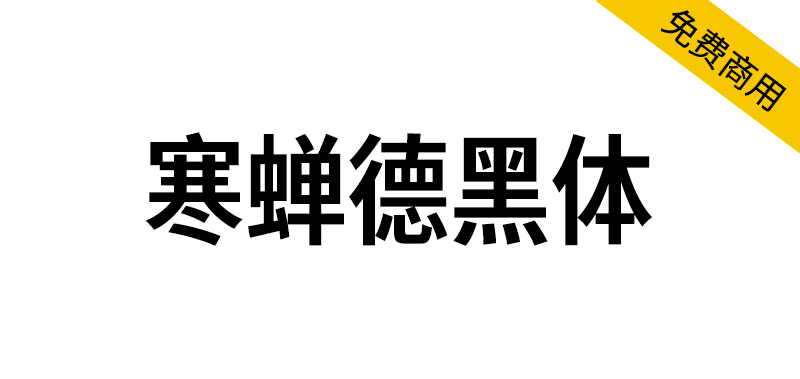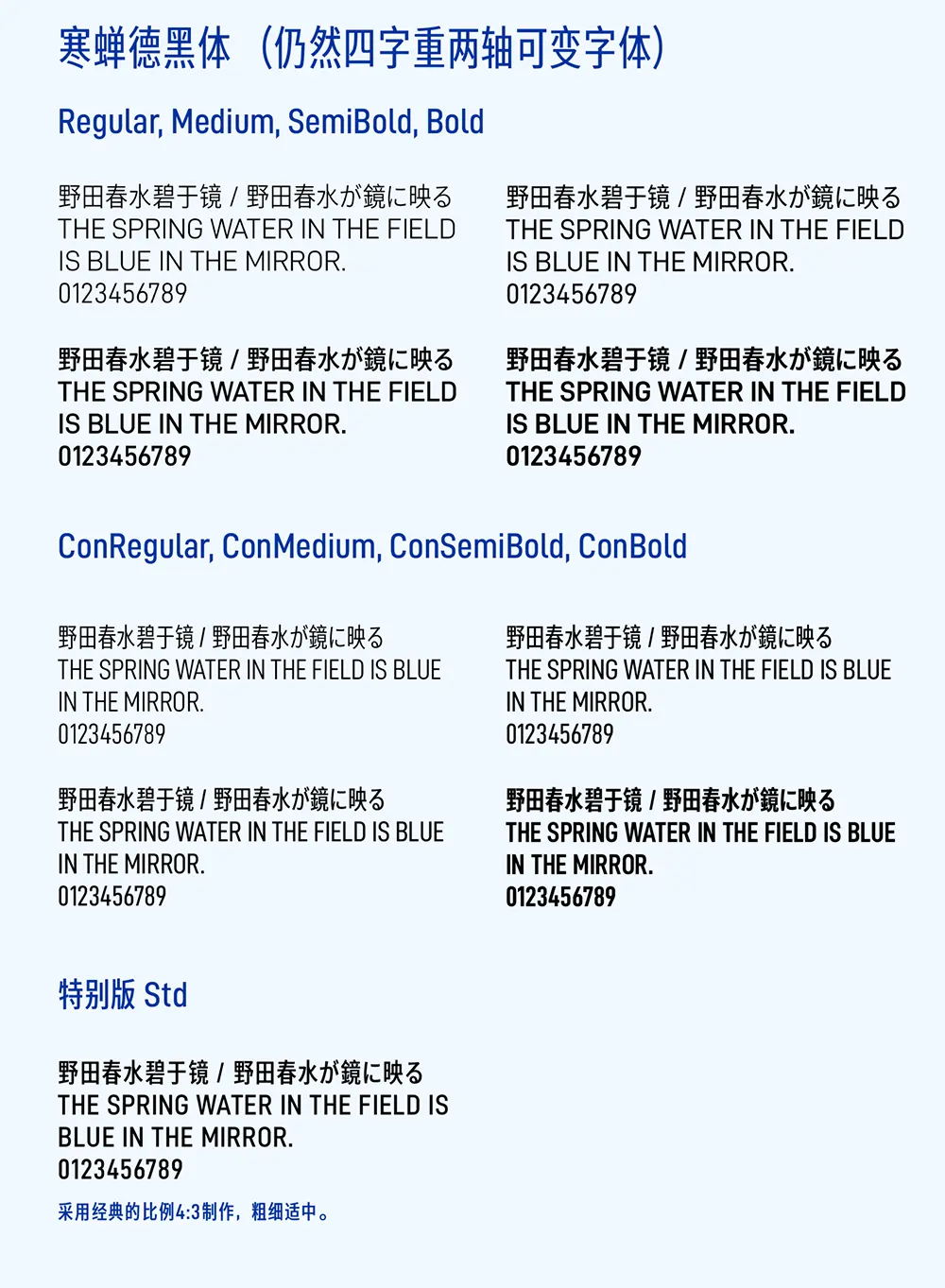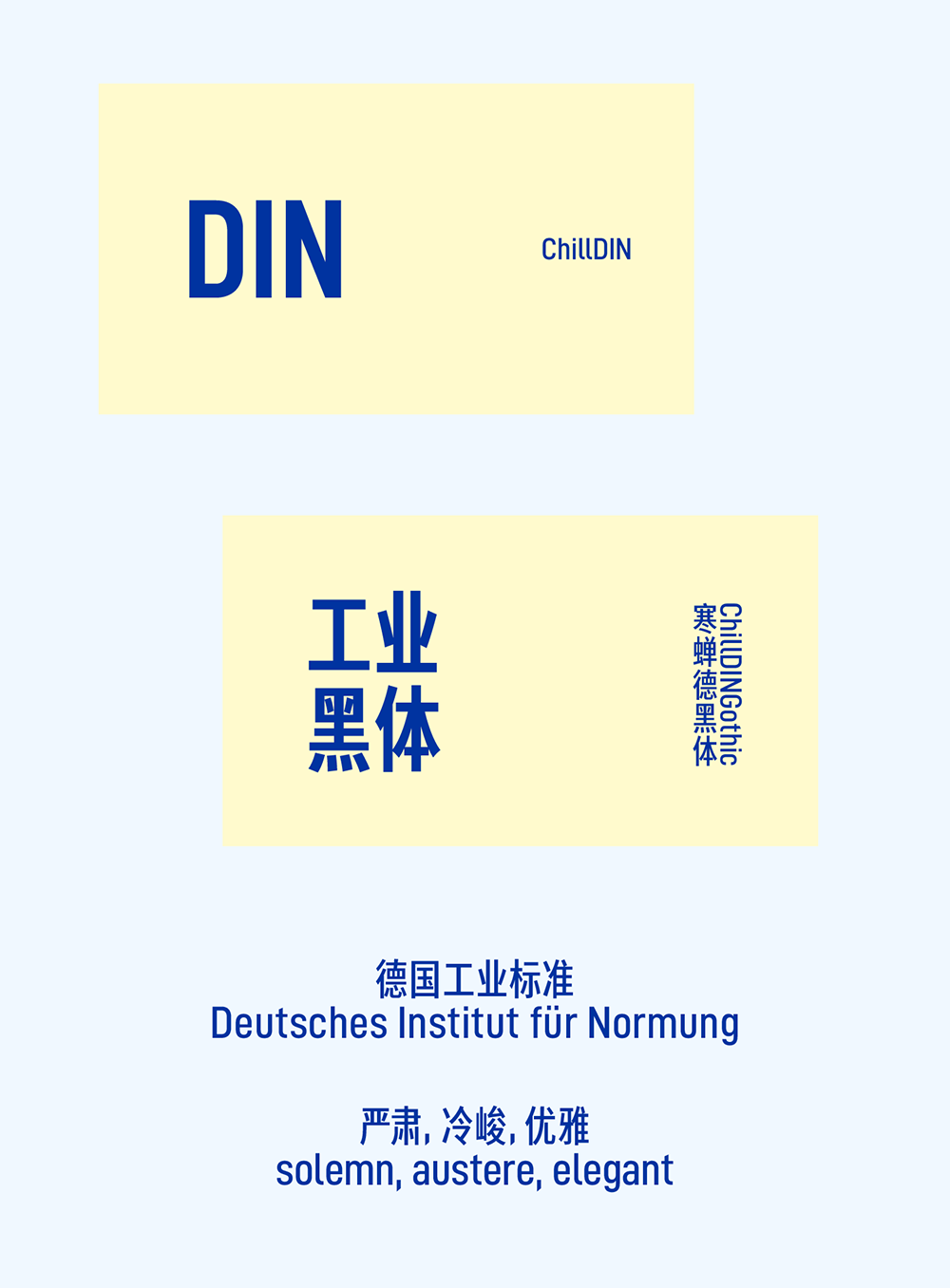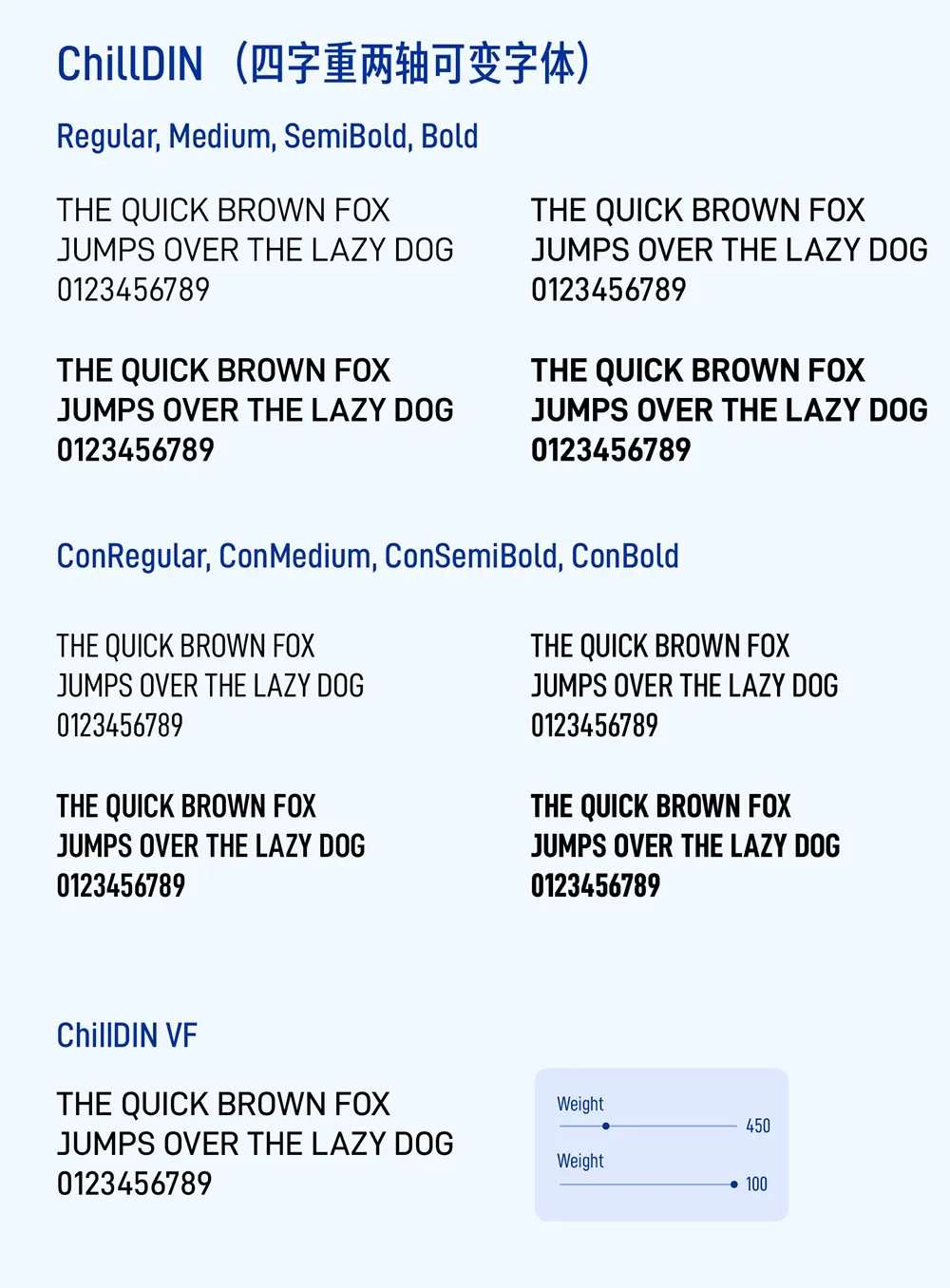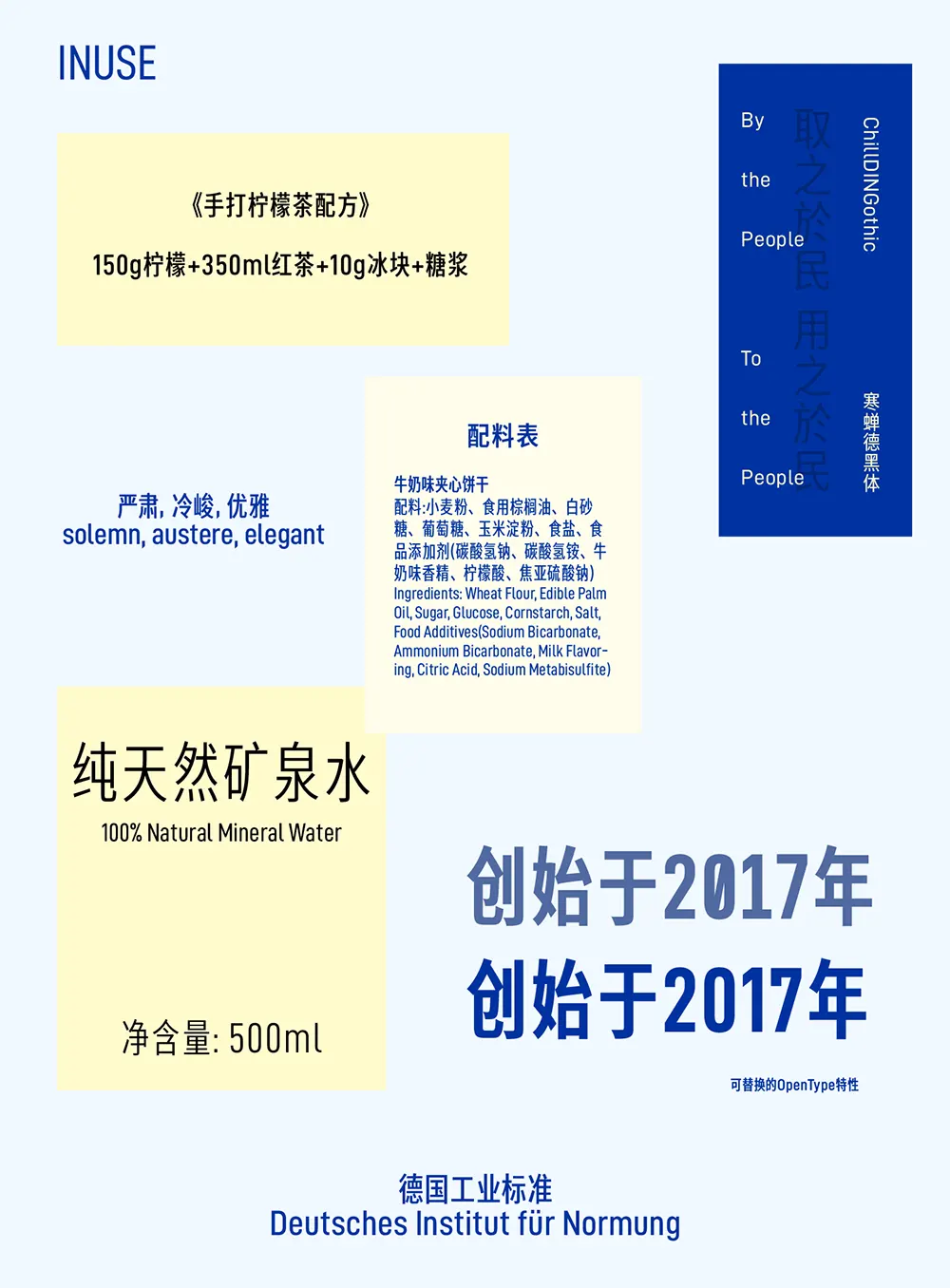
【寒蝉德黑体】源于德国工业标准字体“DIN”,基于D-DIN的修缮
你是否在寻找一款既硬核又免费可商用的德系工业风字体?寒蝉德黑体,源自德国标准DIN字体,基于D-DIN修缮优化,融合思源黑体结构与精准标点设计,兼具机械美感与实用性能。支持个人与企业自由使用、修改甚至捆绑分发,仅需遵守SIL OFL 1.1协议。真正开源、可商用、无法律风险的高质量中文字体方案,究竟长什么样?点击揭晓。
【寒蝉德黑体】源于德国工业标准字体“DIN”,基于D-DIN的修缮
ChillDIN与寒蝉德黑体,来源于德国工业标准字体“DIN”,基于D-DIN的修缮,其中中文字体的搭配从来源寒蝉端黑体思源黑体),修改了参数和标点融合。
【寒蝉德黑体】源于德国工业标准字体“DIN”,基于D-DIN的修缮